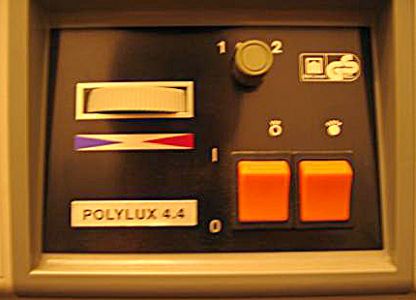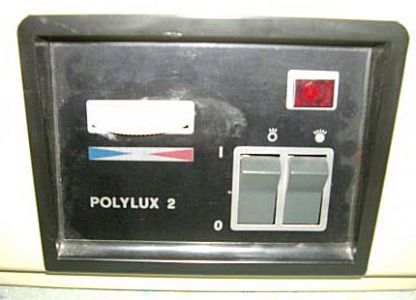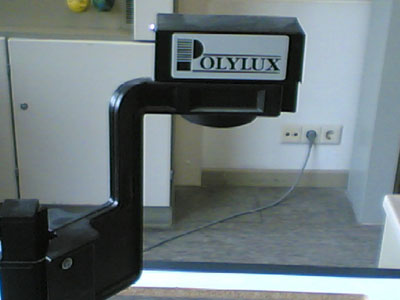
Schrift "Polylux" vom alten Ost-Overheadprojektor
ich habe ein Problem, ich suche die Schriftart, mit der "Polylux" auf den alten Ost-Projektoren stand. Ich habe nichts im web gefunden. Ich weiss nicht mal, wie die aussieht. Soll in Versalien gewesen sein. Hat jemand eine Idee...
War das ne Standart-Schrift?
so sahen die aus:
aber wie die schrift aussah, keine ahnung. war das eine migrogamma
oder so? ich weiss nur noch das es tierisch spaß gemacht hat, während
des unterrichts lineale ode stifte in den ventilator zu halten damit dieser
anhält und der polylux ausgeht.
hier gibts noch die neure ausführung, aus mit logo.
aber frag doch mal
die anbieter nach einem foto des logos.
ja der erste ist es, das erste modell von dem ding. kann mich auch noch gut an die ewige einstellerei bis das bild scharf und am richtigen ort war erinnern;-)
da muss irgendwo polylux draufgestanden haben.
na is halt blöd, wenn man nicht sieht worum es geht...
achso, das von dem heft ist es nicht...
hallo microboy, das ist leider das zweite modell. das was ich meine soll irgendwie ne art gestanzte schrift gehabt haben. aber trotzdem danke
genau den meine ich. is verflixt, ich find auch nix...
@ okela: ne das meine ich auch nit